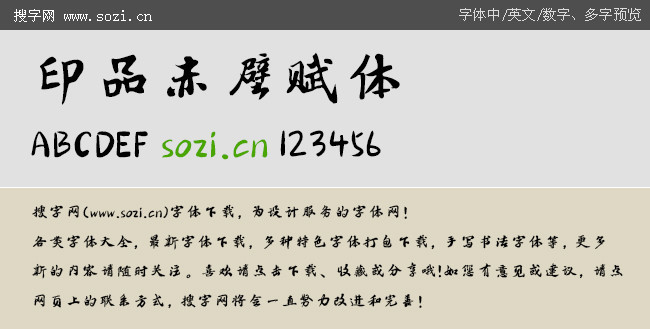
印品赤壁賦體
搜字網(wǎng)給大家提供一款印品赤壁賦體中文字體下載,印品赤壁賦體是一款中文藝術(shù)字體,該字體在布局與結(jié)構(gòu)安排中映現(xiàn)了其獨(dú)特的藝術(shù)構(gòu)思,情韻深致、理意透辟。適用于搭配標(biāo)志、廣告標(biāo)語、商業(yè)廣告等廣告設(shè)計(jì)。